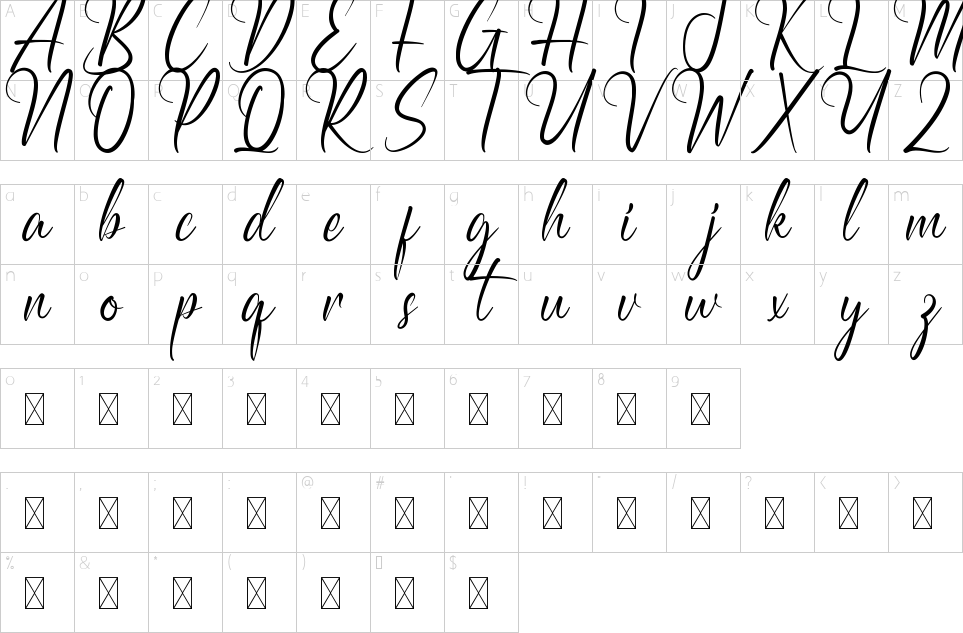
A Marksville Font é uma opção gratuita e elegante para designers digitais e amadores, disponível tanto para Windows quanto para Mac. Desenvolvida pela equipe noahtype, esta fonte vem com uma rica variedade de caracteres, incluindo símbolos especiais e traços, o que a torna versátil para diferentes tipos de projetos. Com seu design minimalista e moderno, a Marksville Font é uma escolha ideal para criar textos agradáveis e de alta qualidade. Se você está em busca de uma fonte gráfica de alta qualidade para seus projetos, sem precisar gastar dinheiro, a Marksville Font é uma excelente opção. Com um total de 1,807 downloads, é fácil ver o quanto os designers apreciam a facilidade e qualidade desta fonte. Sem dúvidas, a Marksville Font é uma ótima adição a seu conjunto de ferramentas gráficas.